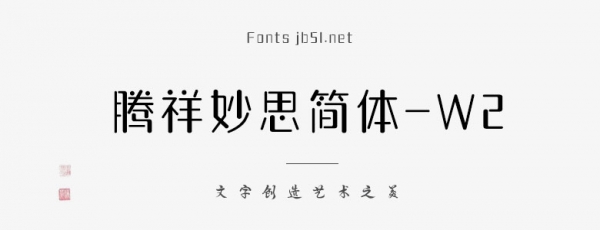
騰祥妙思簡(jiǎn)體-W2是一款不錯(cuò)的藝術(shù)字體,由騰祥字庫(kù)出品,筆畫(huà)斷連輾轉(zhuǎn),粗細(xì)藏露變化,相映成趣;字形俊雅,風(fēng)格獨(dú)特,適合應(yīng)用于藝術(shù)設(shè)計(jì)、平面宣傳設(shè)計(jì)、網(wǎng)頁(yè)設(shè)計(jì),書(shū)法字帖等領(lǐng)域,需要的朋友可以前來(lái)本站下載。
此款字風(fēng)格為美術(shù)字體。妙思W2為系列字庫(kù)中一款,適用于標(biāo)題、小標(biāo)題及正文。筆畫(huà)斷連輾轉(zhuǎn),粗細(xì)藏露變化,相映成趣;字形俊雅,風(fēng)格獨(dú)特;筆畫(huà)凝練簡(jiǎn)潔巧妙構(gòu)思、字形結(jié)構(gòu)修長(zhǎng)、整幅字給人以樸實(shí)無(wú)華,清新秀麗之感。設(shè)計(jì)師以輕松的筆調(diào)詮釋出整款字體的風(fēng)韻,筆畫(huà)聚散有致,沉靜閑適,妙語(yǔ)空傳醉墨香……